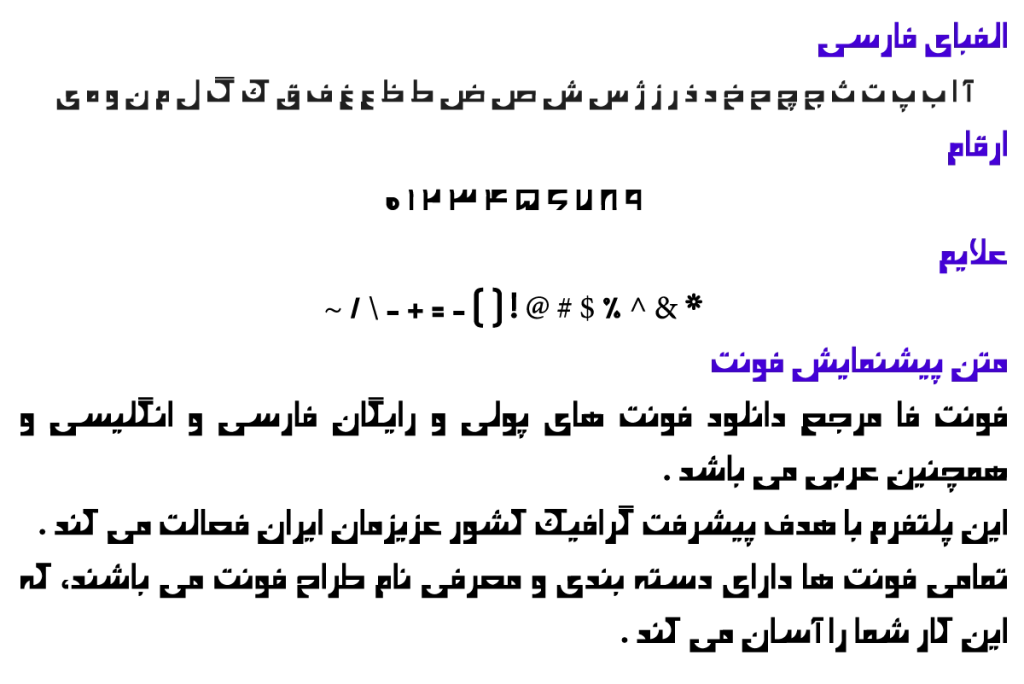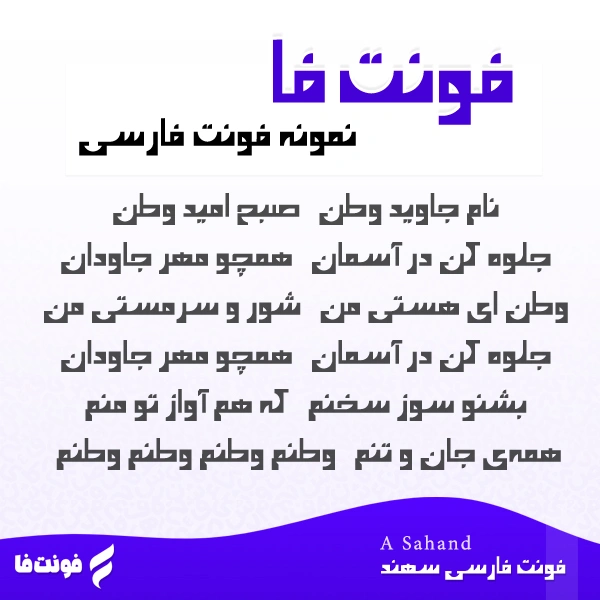
فونت فارسی سهند – A Sahand
سال ساخت فونت: 1392
طراح فونت: مجتبی کیا نوع فونت: فونت هندسی
پیشنمایش فونت سهند
توضیحات و معرفی فونت سهند
فونت فارسی سهند ( A Sahand ) از مجموعه فونت های آزاد می باشد، و نیز نوع فونت هندسی می باشد.
فونت خوشگل مربوط توسط مجتبی کیا در سال 1392 طراحی و ساخته شده است.
و نیز فونت A Sahand در یک وزن پر رنگ است.
- A Sahand Bold
در تصویر زیر، پیش نمایشی از این تایپ فیس را همراه با شعر زیبای فارسی میبینید.